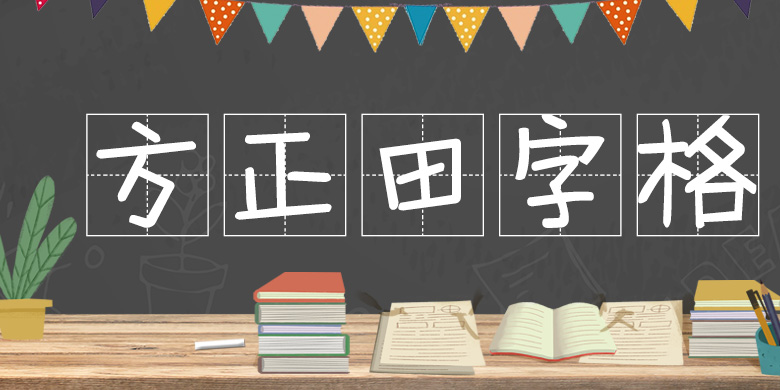
字体介绍 品牌:方正手迹设计师:王霖发行时间:2017字库编码:大陆简体(GB2312-80)分类:创意书写字体属性:精品字 英文名称:FZSJ-TIANZG.TTF 方正田字格体,稚气未脱的字形搭配着儿时作业本上的田字格,仿佛自己又回到了纯真美好的幼时时光。适用于少儿类书籍、文化类宣传设计、综艺字幕、品牌广告和产品包装设计,以及社交网络的个性化用字。 字体下载 官方下载